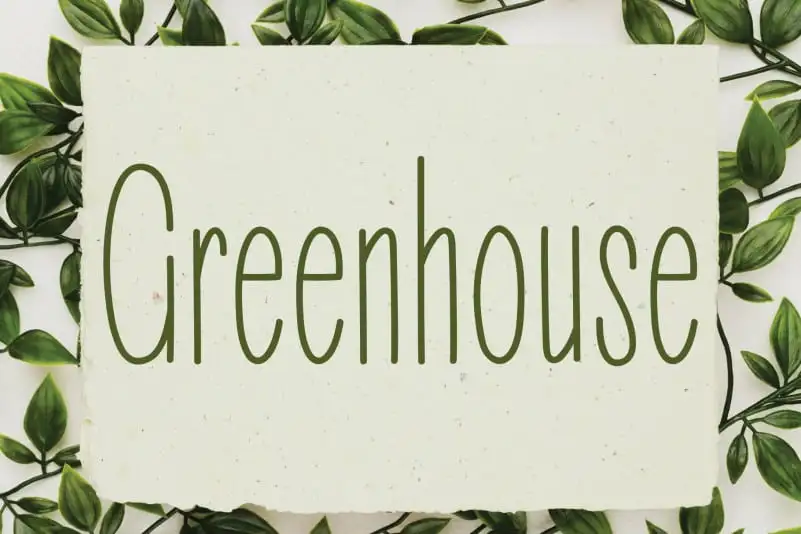
Greenhouse Handwritten Font – Download Grátis
A Greenhouse Handwritten Font é a escolha perfeita para aqueles que buscam uma fonte escrita à mão que traz uma leve sensação de tranquilidade e naturalidade ao design. Especialmente criados como produtos únicos, este tipo de letra foi projetado para oferecer um experiência única e excepcional aos usuários. Com sua característica autêntica e detalhada, a Greenhouse Handwritten Font é perfeita para aplicativos que exigem uma aparência elegante e pessoal. Suas linhas sutis e os traços delicados criam um efeito calmo e natural, capaz de complementar textos em variadas aplicações, desde design gráfico até criação de branding personalizado. Ideal para qualquer projeto que valorize a serenidade e a harmonia natural, a Greenhouse Handwritten Font é a escolha certa para designers buscando uma fonte única e versátil. Com sua delicadeza e sofisticação combinadas em perfeição, ela é um verdadeiro prazer de usar, adicionando um toque único à qualquer projeto que adorne.